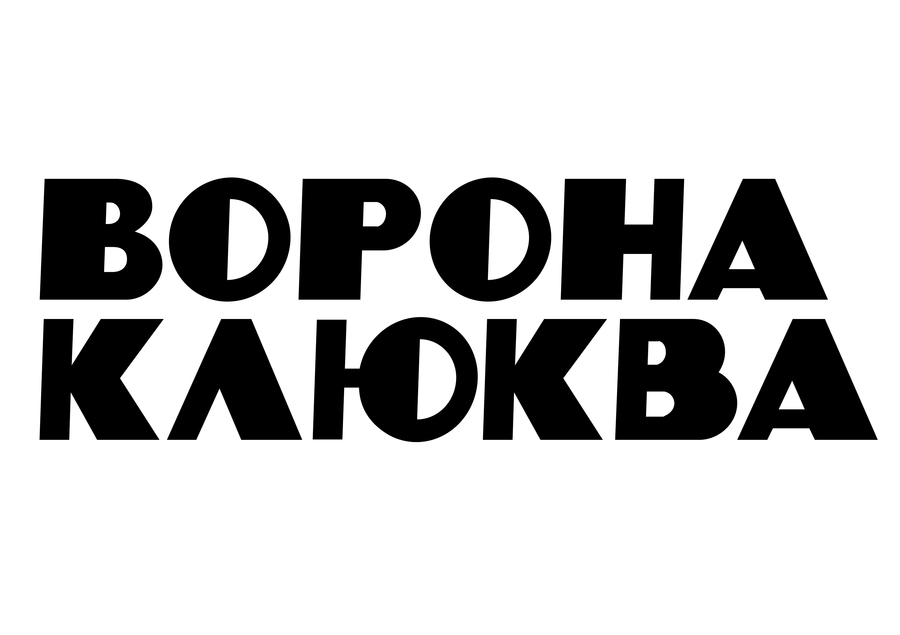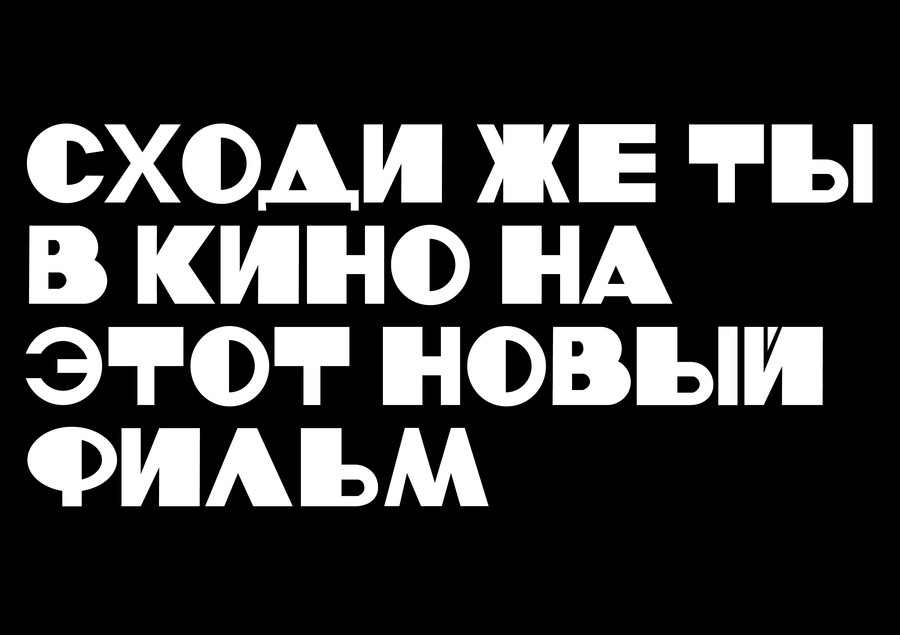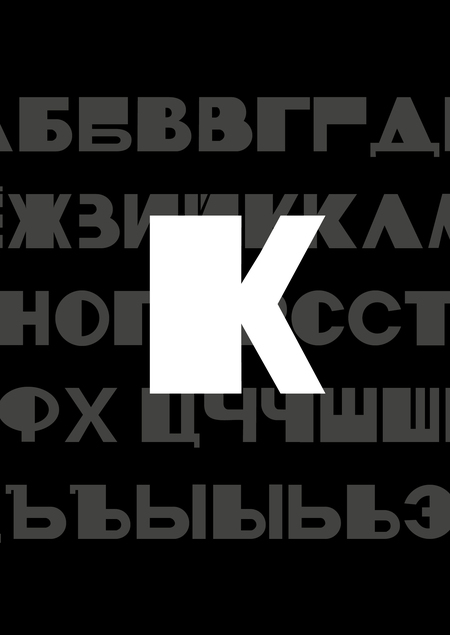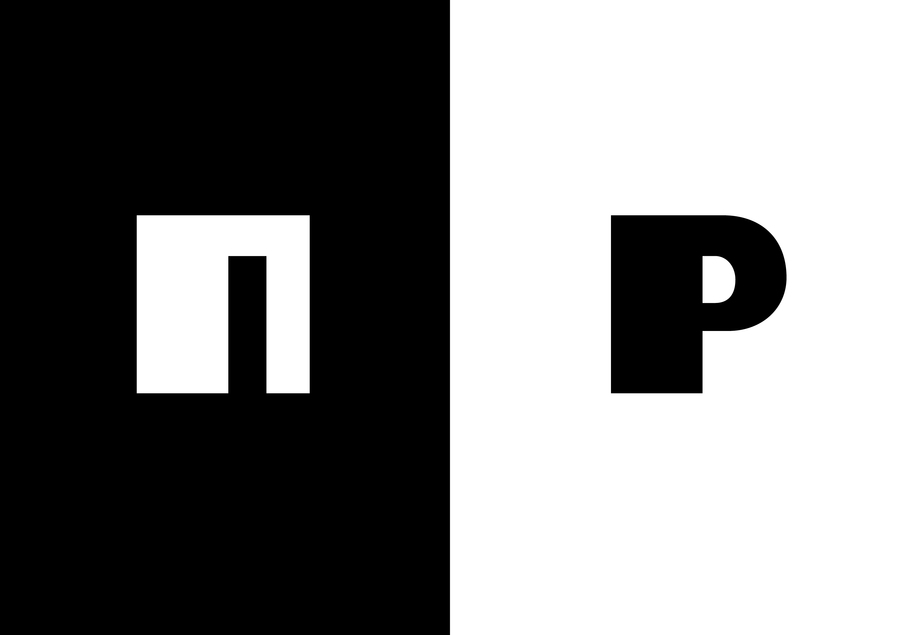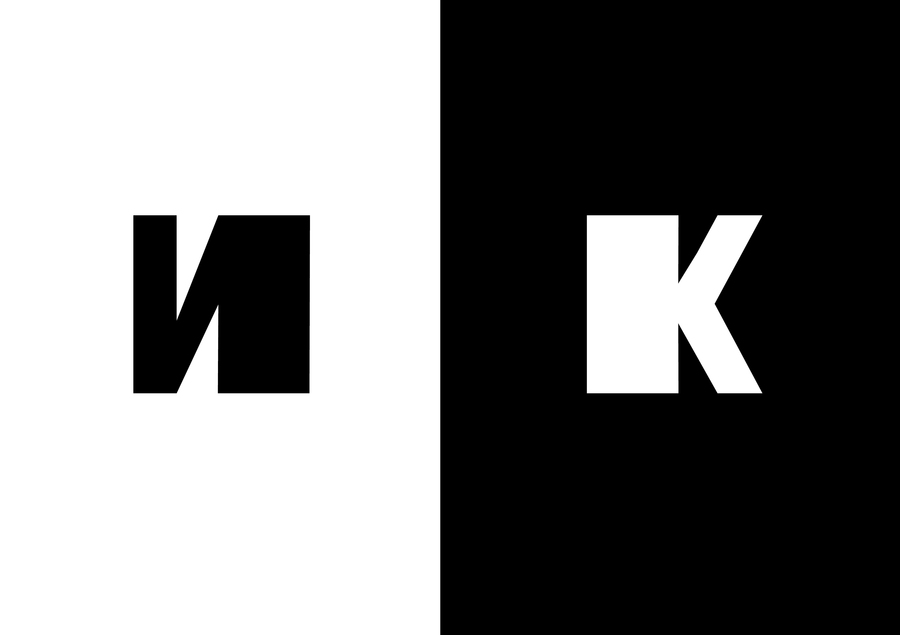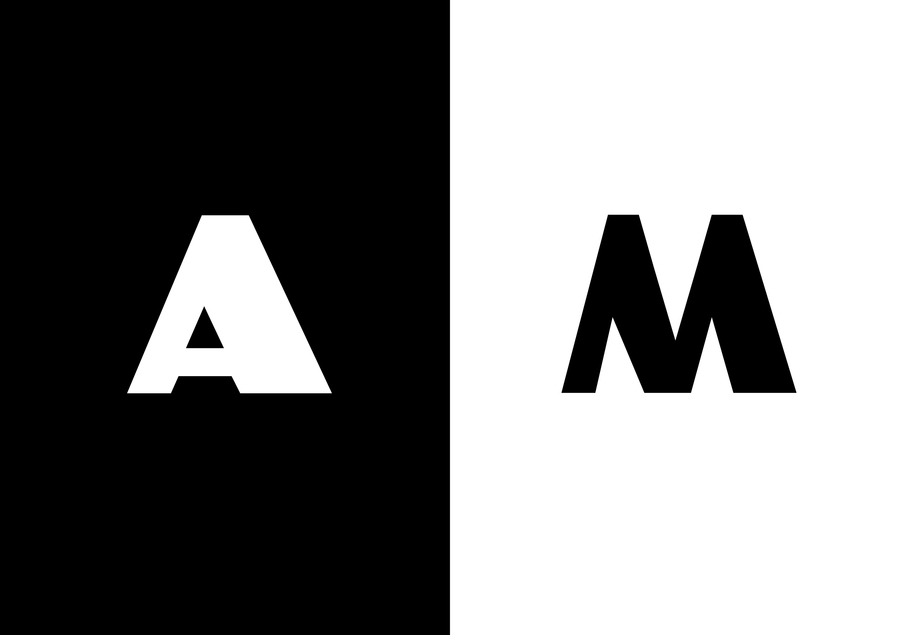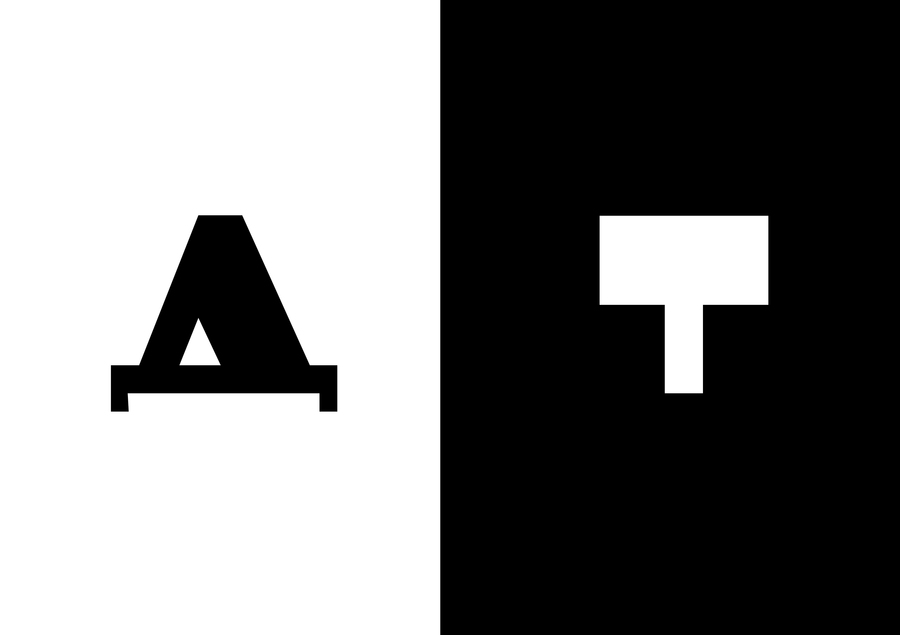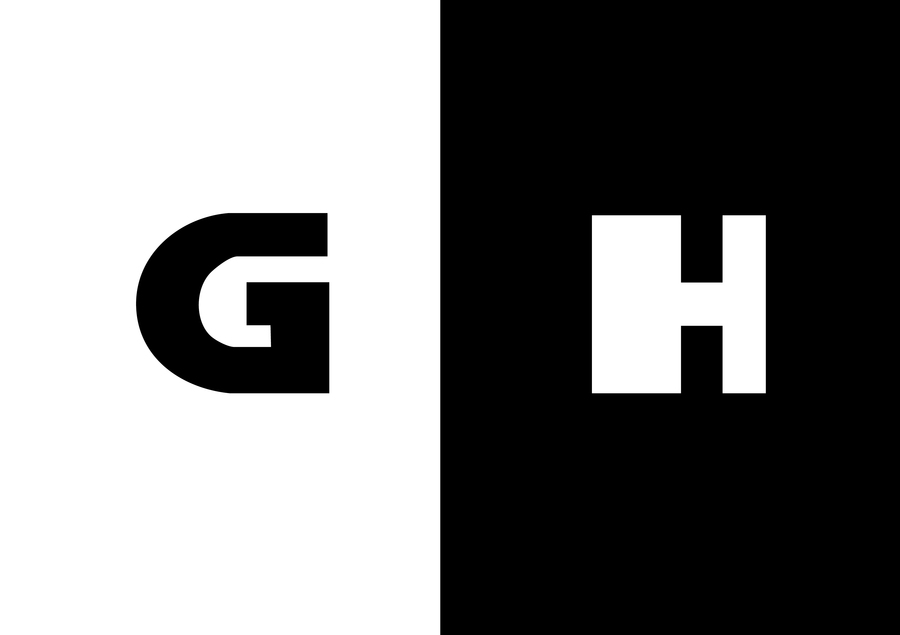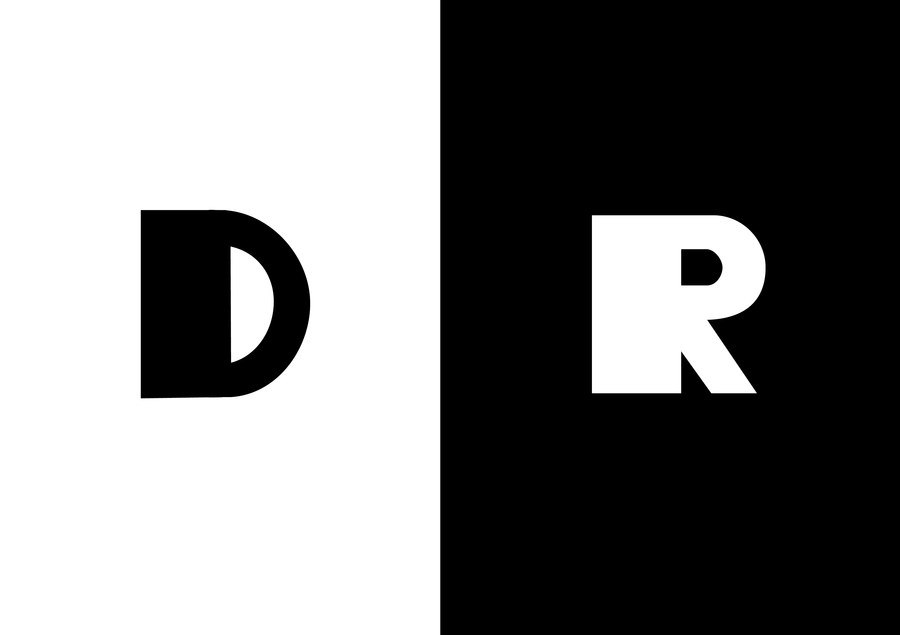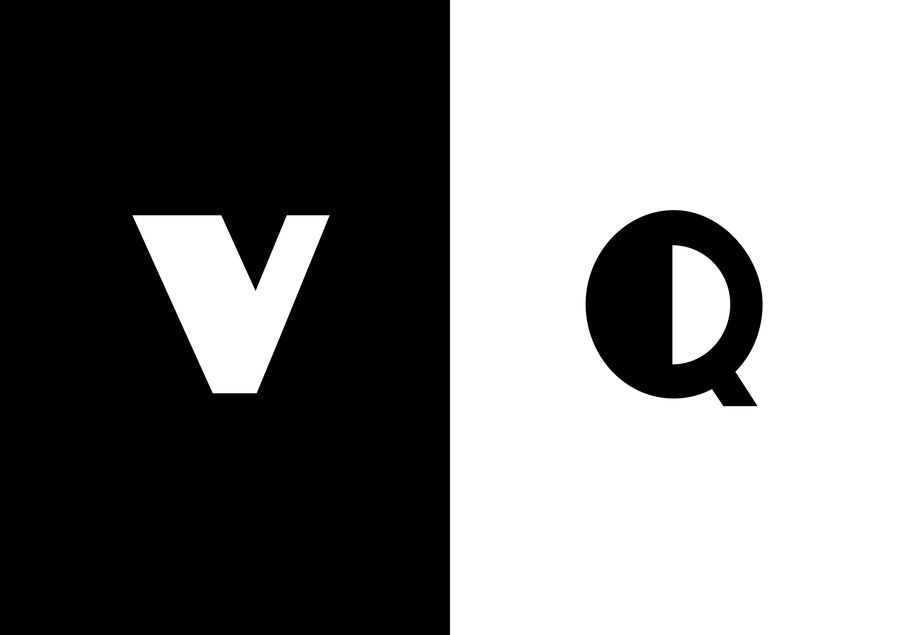
Шрифт построен на контрасте монументальности и разрезанной формы. Буквы выглядят устойчивыми и массивными, c внутренней динамикой — словно они находятся в процессе трансформации. Концепция — типографика как объект, а не просто носитель текста. MODULE TT работает почти как графический элемент и способен задавать характер всей композиции.
Основа — геометрический гротеск с практически монолинейным штрихом. Пропорции стремятся к устойчивым, с расширенными формами, что усиливает плакатность.